Font huruf kapital (all caps fonts) adalah font huruf besar semua.
Jadi, huruf kecil (lowercase) yang kita ketik akan berbentuk huruf besar (uppercase).
Font tipe ini cocok untuk membuat huruf balok dan teks yang singkat seperti tulisan pada poster dan CTA (call to action).
Catatan: nama font yang ada huruf SC merupakan font Small Caps, yaitu font huruf besar tapi kecil ukurannya. Font ini juga dikenal dengan nama small capitals atau petite caps.
Almendra SC
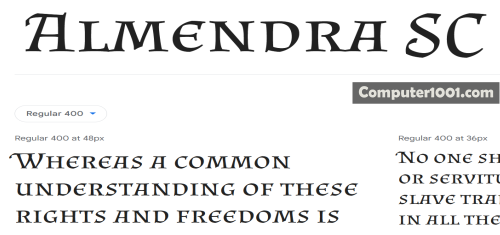
Almendra adalah font kaligrafi yang bernuansa gotik. Sangat cocok untuk judul buku cerita anak-anak.
Amatic SC
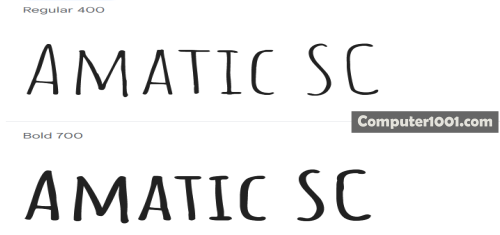
Font Amatic adalah font huruf besar yang tinggi, ramping, dan mirip tulisan tangan.
Alegreya Sans SC
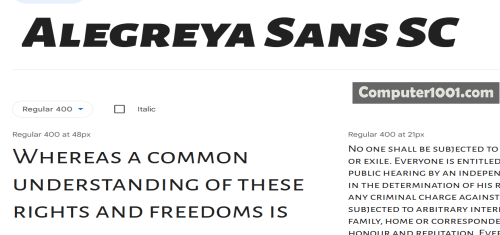
Alegreya Sans SC adalah font Small Caps bentuk sans serif, yang merupakan pelengkap font Alegreya Sans.
Font ini memiliki 14 gaya, mulai dari huruf yang sangat tipis hingga yang tebal italic.
Alegreya SC
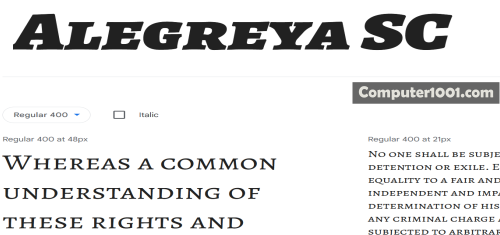
Alegreya SC, yang merupakan pelengkap font Algreya, adalah font Small Caps bentuk serif yang didesain untuk memudahkan pembacaan teks yang panjang.
Font ini memiliki 10 gaya, mulai dari huruf yang tebalnya reguler hingga yang ekstra tebal.
Bruno Ace SC
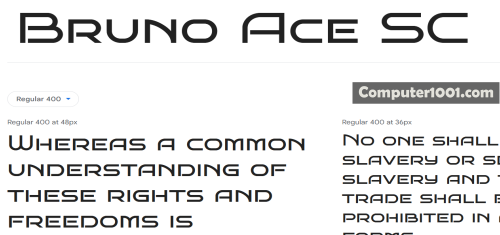
Font Bruno Ace mengambil inspirasi dari logo otomotif modern.
Bowlby One SC
Bowlby One SC sangat cocok untuk desain judul yang besar dan tebal dengan tampilan yang mencolok.
Cormorant SC
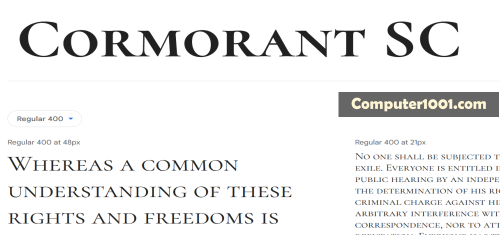
Cormorant adalah font serif yang elegan dan memiliki 5 ketebalan.
Diplomata SC
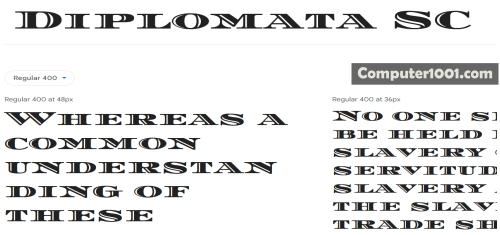
Diplomata adalah font display yang keren dan cocok untuk judul atau teks yang singkat.
Anda bisa menggabungkannya dengan font Diplomata ini yang ada huruf kecil.
Encode Sans SC
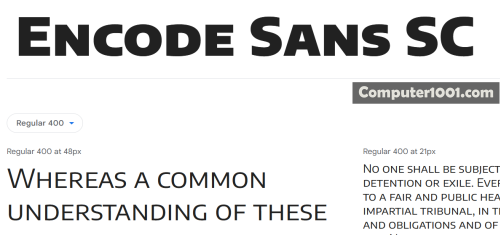
Encode Sans adalah font sans-serif yang serbaguna dengan bentuk huruf yang sederhana, tajam, dan mudah dibaca.
Holtwood One SC
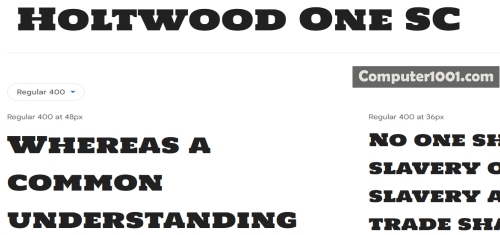
Holtwood adalah font display tebal yang dikembangkan untuk digunakan dengan browser web modern dan dapat digunakan untuk ukuran teks yang besar dan tebal.
IM Fell Double Pica SC
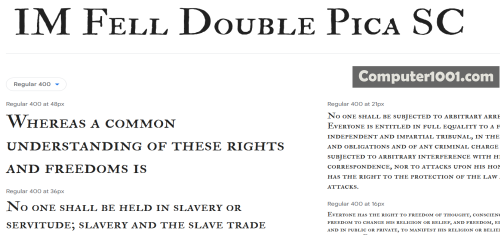
IM Fell English SC
IM Fell French Canon SC
IM Fell Great Primer SC
Marcellus SC
Marcellus SC adalah jenis font huruf serif lebar, yang terinspirasi oleh bentuk huruf prasasti Romawi klasik yang indah.
Mate SC
Font Mate memiliki struktur yang sederhana dan tajam. Cocok digunakan dalam teks, namun juga bisa untuk judul yang besar.
Patrick Hand SC
Patrick Hand adalah font yang dibuat berdasarkan tulisan tangan desainernya sendiri. Ia dikembangkan untuk menghadirkan efek tulisan tangan yang keren pada teks dan juga bisa untuk judul.
Font ini juga memiliki angka 0 – 9, tanda kurung, dan tanda baca.
Playfair Display SC
Playfair Display SC adalah font huruf besar aesthetic dengan 6 ketebalan huruf.
Spectral SC
Spectral SC adalah font kapital kecil yang elegan dengan 7 ketebalan huruf, mulai dari ekstra tipis sampai ekstra tebal.
Vollkorn SC
Ysabeau SC
Bebas Neue
Bebas Neue adalah font display yang cocok untuk judul, caption, dan kemasan.
Bungee
Bungee adalah font display yang didesain untuk papan tanda dengan 5 variasi seperti yang disajikan dalam postingan ini.
Bungee Hairline
Bungee Inline
Bungee Outline
Bungee Shade
Cinzel
Cinzel adalah jenis huruf yang terinspirasi dari prasasti Romawi abad pertama. Font yang elegan ini memiliki 6 ketebalan.
Montserrat Subrayada
Huruf-huruf pada font Montserrat Subrayada memiliki sambungan garis bawah.
Permanent Marker
Font ini memiliki tampilan seperti ditulis tangan dengan menggunakan spidol.
Rubik Mono One
Rubik Mono One adalah font sans serif tebal dengan sudut agak melengkung.
Six Caps
Six Caps adalah font yang tampilannya tinggi ramping, dengan jarak huruf yang rapat.
Kablammo
Kablammo adalah font yang angka dan hurufnya memiliki desain yang unik, karena terinspirasi oleh font Jokerman serta kartun dan mainan di era 80 dan 90-an.
Font ini juga memiliki beberapa pattern yang cantik, emoji, dan simbol astrologi.
Silkscreen
Silkscreen adalah font huruf piksel bergaya retro. Ada 2 bobot, yaitu yang reguler dan tebal.
Trade Winds
Trade Winds adalah font dengan gaya huruf yang terdistorsi, pinggiran yang tidak rata dan kasar.
Cocok untuk desain yang berkesan santai namun terstruktur pada branding / proyek Anda.